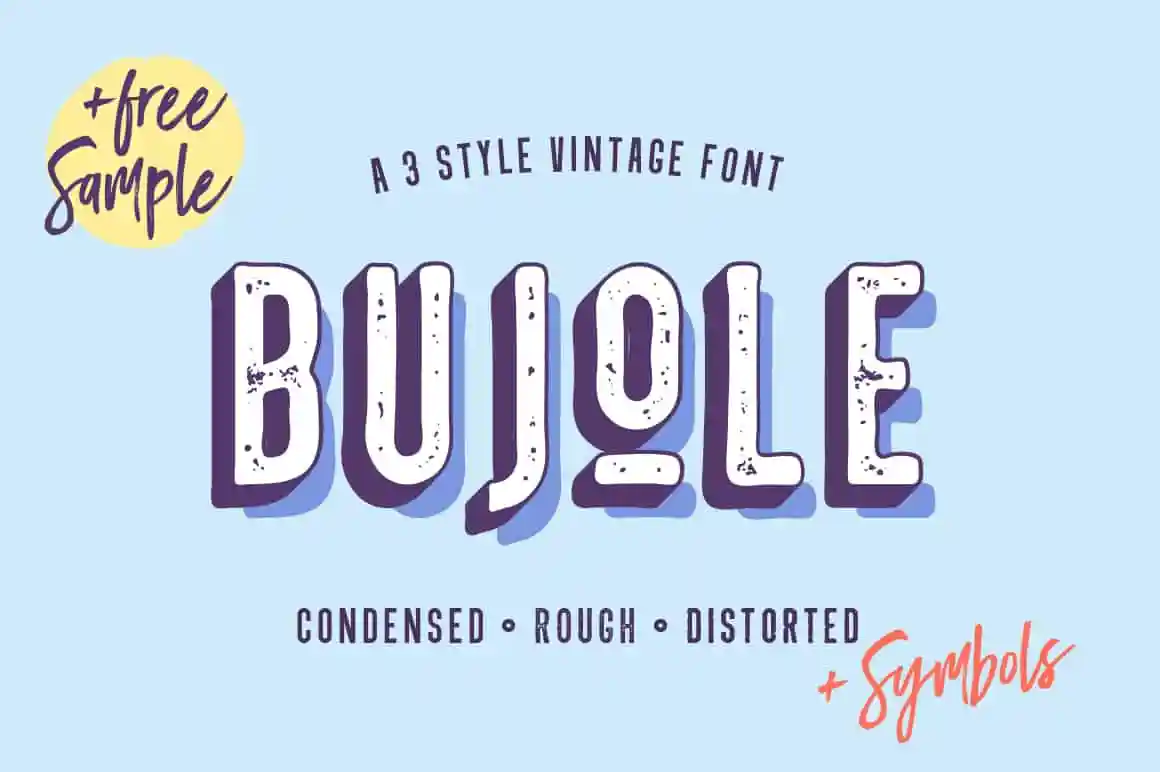
Introduzimos à você Bujole – A 3 Style Vintage Font, uma nova opção para designers gráficos interessados no estilo vintage. Desenvolvida pelo designer VladCristea, esta font vem inspirada nos anos passados e conta com três estilos distintos: Condensado, Rough (rupestre) e Distorcido. Ideal para criação de logotipos, selos ou rótulos, embalagens design, headlines ou mesmo anúncios, Bujole é uma escolha perfeita para qualquer projeto gráfico. Este estilo vintage oferece um toque único que traz vida a suas produções. Seja você um amante de estilos clássicos ou alguém que procura algo mais moderno e vintage ao mesmo tempo, certamente vai encontrar Bujole – A 3 Style Vintage Font útil para seus projetos design.